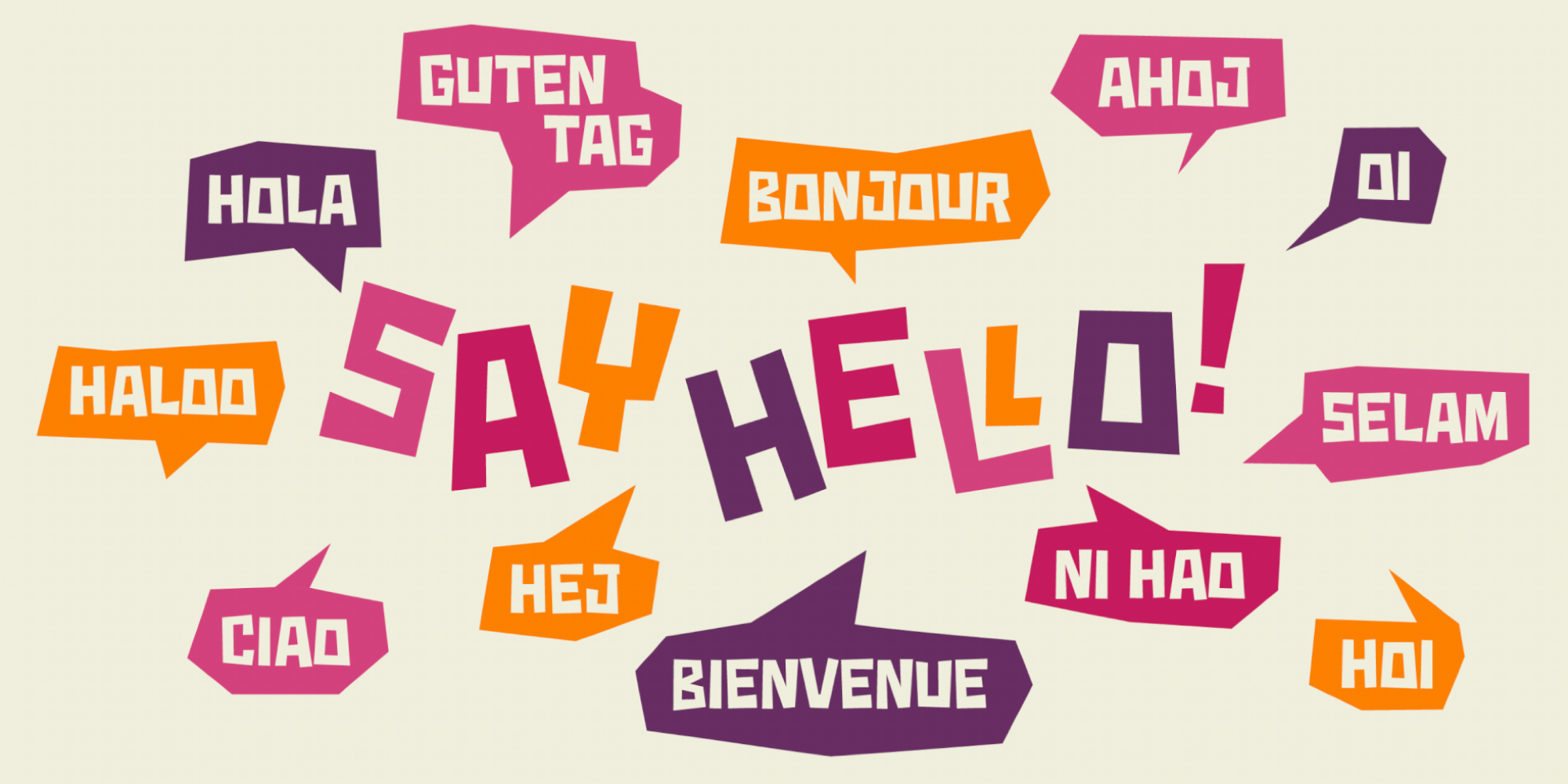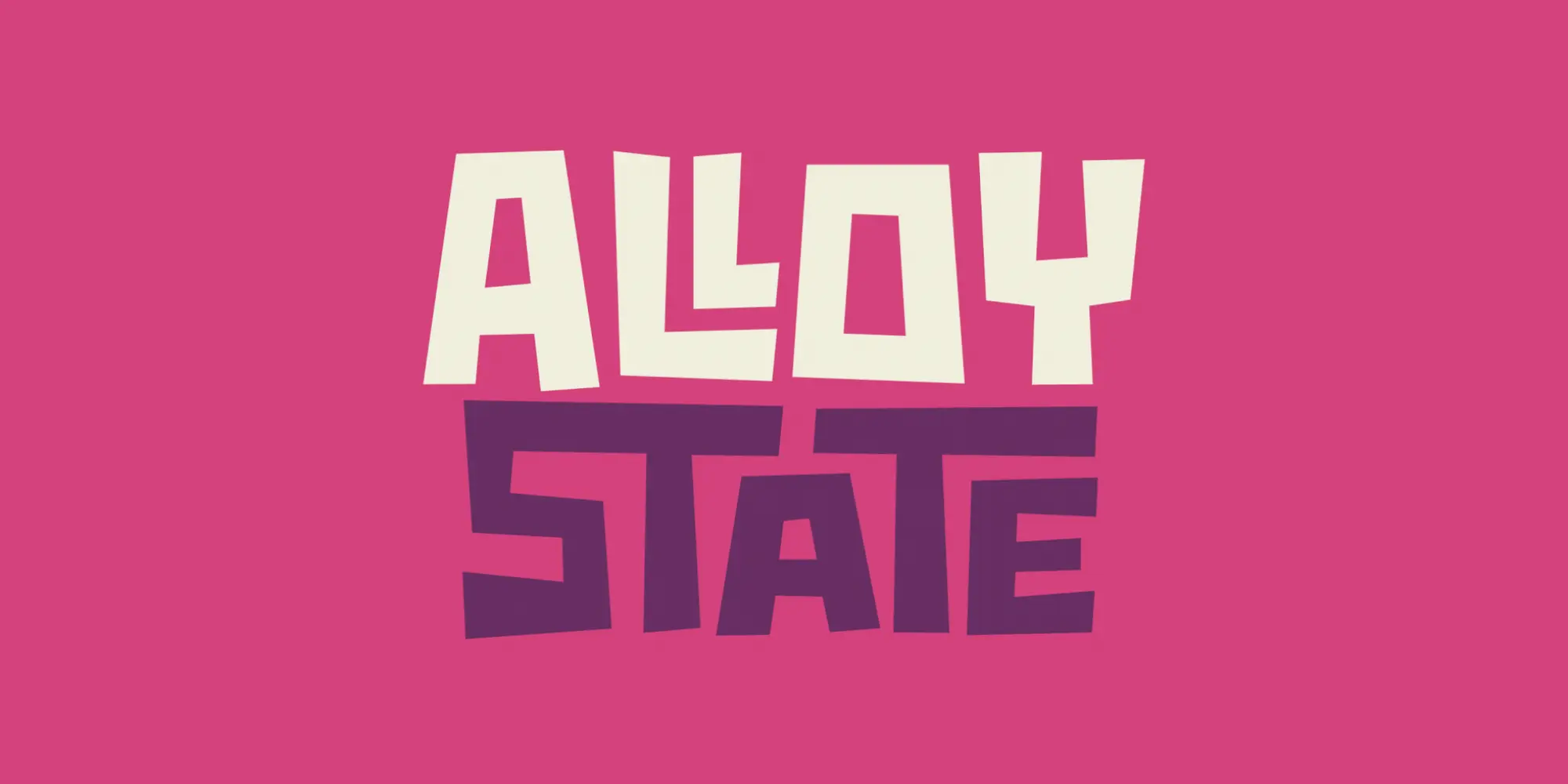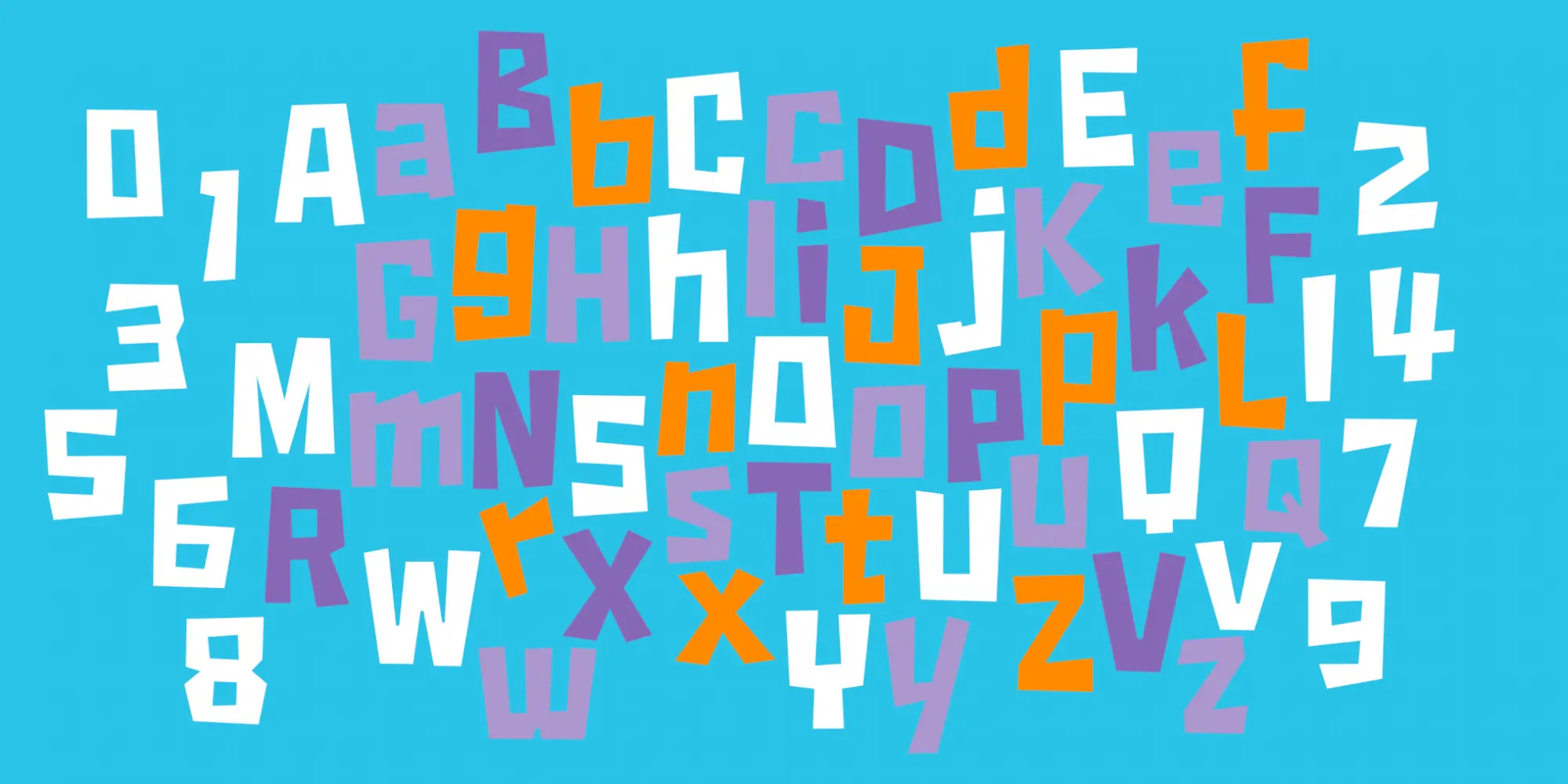
Font-Wiki: Fido Pro
Die Fido von Patrick Griffin erschien 2009 über Canada Type. Die Schrift im Papierschnitt-Stil ist in einem Schnitt und mit über 100 Ligaturen verfügbar, die die Zeichenformen ineinander verschränken. Die Schrift wurde 10 Jahre nach der ursprünglichen Veröffentlichung noch einmal zur Pro-Version ausgebaut und enthält nun auch eine kyrillische und griechische Zeichenbelegung.